11.6 Capas
Se puede obtener tres tipos diferentes de capas que proporcionan diferentes niveles de opacidad: opaco, translúcido y transparente. El cambio de los niveles de opacidad puede ayudar a determinar las capas visuales de arriba abajo, o de delante a atrás.
Opaco hace referencia al estar de opacidad total cuando, en las letras, palabras o formas con capas, la opaca mas superior cubre y bloquea completamente a las capas inferiores. En los siguientes ejemplos, aparece el trabajo con un color simple o con combinaciones de la paleta positivas – negativas.
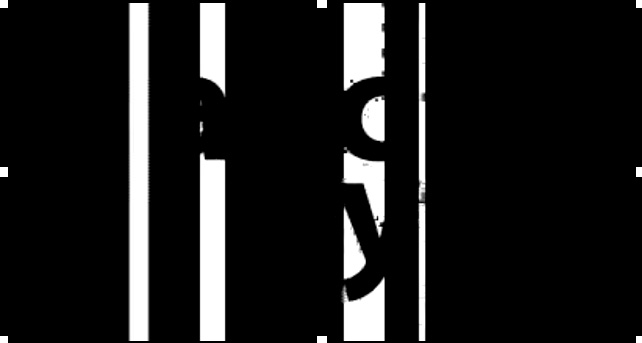
El estado traslúcido de opacidad consigue cuando se filtra algo de luz. Hay diferentes valor de translucidez y cuando se disponen en capas múltiples letras y palabras translúcidas, sucede un efecto óptico de tipo fantasmal, que tiene como resultado combinaciones de letras extrañas. Cuando los colores son traslúcidos y se superponen, se mezclan en tiempo real.
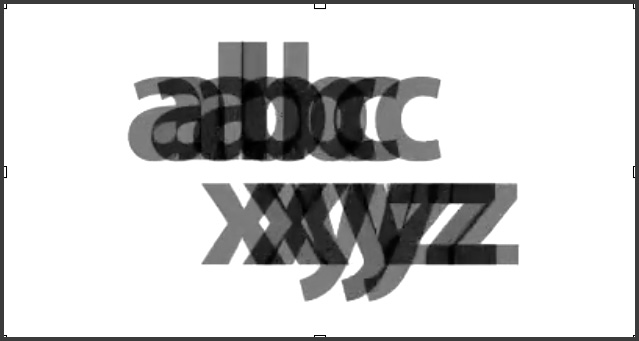
Trasparente es el estado de opacidad en el que los elementos dispuestos en capas aparecen huecos. Las letras delineadas y las perforadas permiten que las capas se vean completamente.
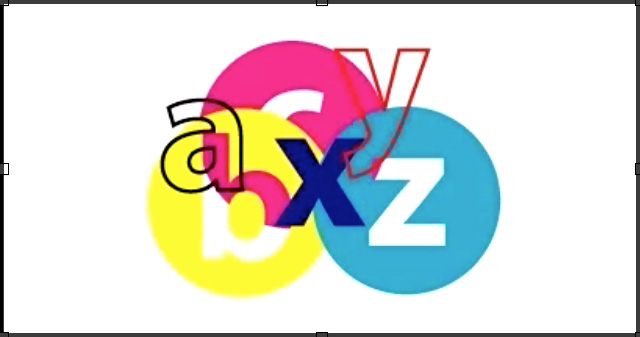
La opacidad también puede ser efectiva en las imágenes de tono continuo; en este caso, un video desenfocado o luces de colores funcionan como un fondo en el que las letras translúcidas y transparentes permiten que la luz traspase y se difunda a diferentes niveles.